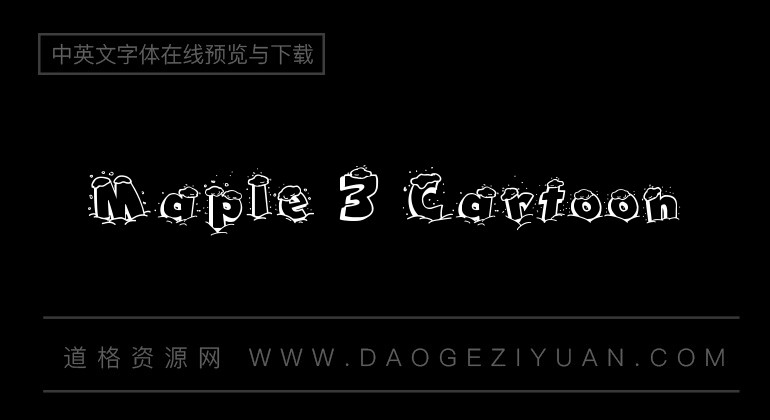
Maple 3 Cartoon
Maple 3 Cartoon 字体是一款具有轻松可爱的特色的卡通字体,它的字体设计灵感来自于日本动漫,由知名字体设计师 Maple 3 创作,它具有细腻的线条,清晰的字形,以及多种可爱的曲线,可以给设计师带来无限的创意空间。它适合用于各种海报、广告、品牌标志等设计,也可以用于儿童产品、游戏、动画等设计中。
Maple 3 Cartoon是一款非常不错的手写艺术字体,具有很好的视觉感,适合于文化类的宣传设计、商业类品牌的广告和产品包装设计以及个性化文字排版等较多场景。